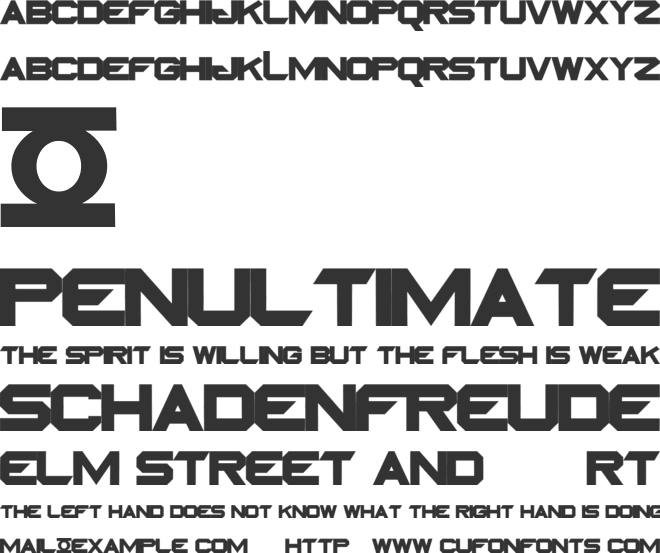
GREEN LANTERN MOVIE Font
P. A. Vannucci
Direttamente dal film diretto da MARTIN CAMPBELL e interpretato da RYAN REYNOLDS, il font inedito per tutti gli estimatori del film.
Directly from the film directed by MARTIN CAMPBELL and starring RYAN REYNOLDS, the new font for all admirers of the film.